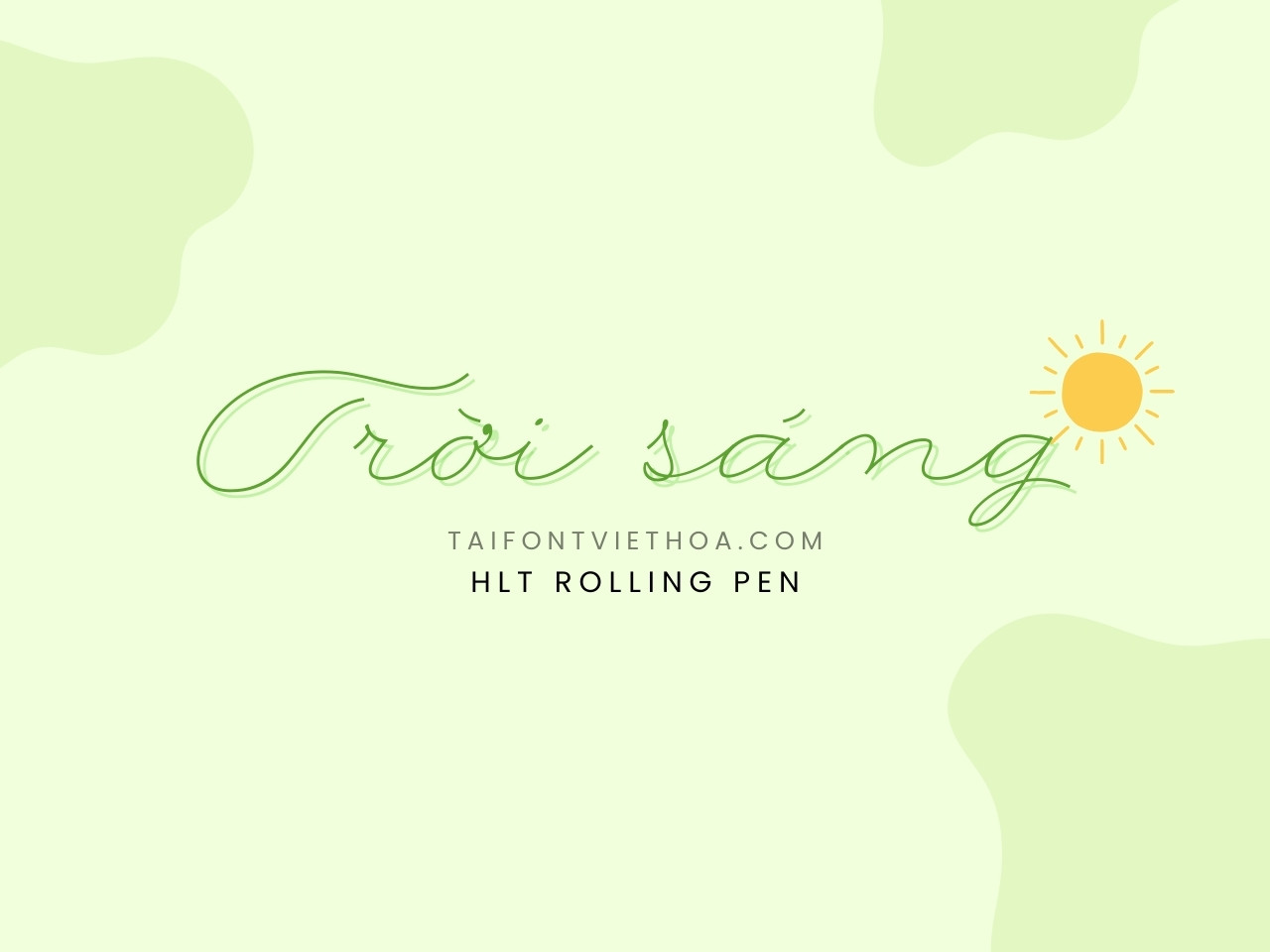
Font việt hóa HLT Rollingpen
HLT Rollingpen – Nét chữ viết tay cổ điển với hơi thở hiện đại
HLT Rollingpen là bản Việt hóa của font gốc “Rollingpen” – một kiểu chữ script thủ công đặc trưng, được phát triển bởi Ale Paul – nhà thiết kế typography nổi tiếng đến từ Sudtipos, Argentina. Font gốc mô phỏng nét viết bằng bút mực truyền thống với các đường uốn lượn mềm mại, nhấn nhá tinh tế. Rollingpen không chỉ đơn thuần là một kiểu chữ, mà còn là sự tái hiện hoàn hảo của nghệ thuật thư pháp hiện đại trong thiết kế số. Font hỗ trợ hơn 200 ký tự Latin mở rộng, tương thích với hơn 60 ngôn ngữ.
Phiên bản Việt hóa được nhóm HLT Fonts thực hiện, tối ưu đầy đủ bảng dấu tiếng Việt và các ký tự đặc trưng, giữ lại trọn vẹn tính nghệ thuật và tinh thần bay bổng của thiết kế gốc. Các dấu được điều chỉnh khéo léo để phù hợp với độ nghiêng và độ uốn lượn của chữ, mang lại trải nghiệm thị giác nhất quán cho người dùng Việt. Font này được taifontviethoa.com chọn lọc kỹ lưỡng, thử nghiệm thực tế và chia sẻ nhằm phục vụ cộng đồng thiết kế đang tìm kiếm những font script cao cấp mang hơi hướng thư pháp mềm mại.
Đặc trưng thiết kế và ứng dụng trong thiết kế thương hiệu
Rollingpen nổi bật nhờ hệ thống ligatures phong phú, các nét kéo dài mượt mà, độ dày chuyển biến linh hoạt giữa các nét chính – phụ. Phong cách chữ đậm chất thư pháp giúp tăng tính biểu cảm và cảm giác thủ công, rất thích hợp để tạo điểm nhấn trong các thiết kế mang tính cá nhân, nghệ thuật hoặc cao cấp.
Font phù hợp với nhiều dự án thiết kế: từ logo thương hiệu thời trang, spa, mỹ phẩm đến các sản phẩm bao bì cao cấp, thiệp mời cưới, bìa sách hay typography nghệ thuật. Rollingpen không chỉ là một font chữ mà còn là công cụ truyền tải cảm xúc – yếu tố quan trọng trong nhận diện thương hiệu.